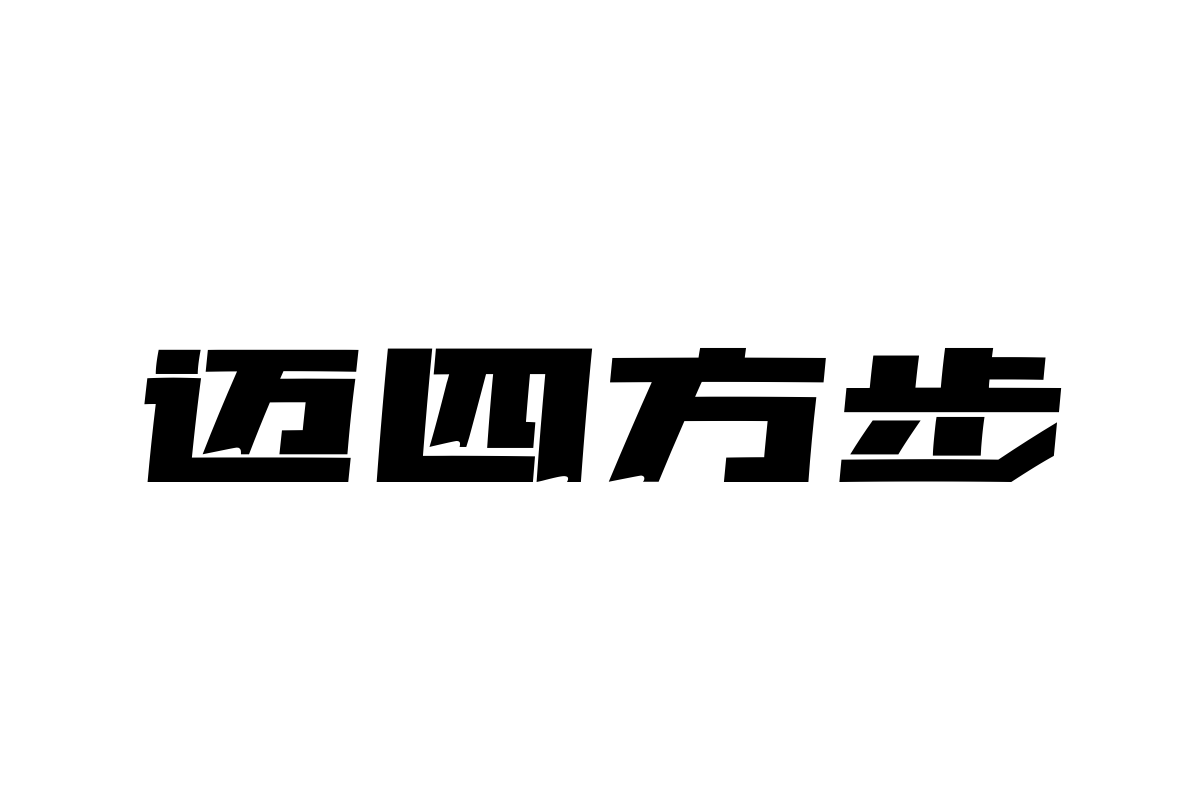
上首极速体是一款专为中文书写设计的字体,具有以下特点:
1. 字形结构独特:上首极速体的字形结构简洁明了,笔画流畅自然,易于阅读。
2. 风格鲜明:上首极速体的设计风格独特,线条粗细适中,既有力度感又不失优雅,适合用于各类文字设计。
3. 适应性强:上首极速体适用于多种应用场景,如广告、宣传、报纸、杂志等,能够满足不同用户的个性化需求。
4. 易用性高:上首极速体采用现代字体设计理念,易于学习和使用,无需专业设计知识即可轻松制作出高质量的文字效果。
总之,上首极速体是一款功能强大、风格独特的字体,适用于各种中文文本设计场景,能够满足用户的不同需求。